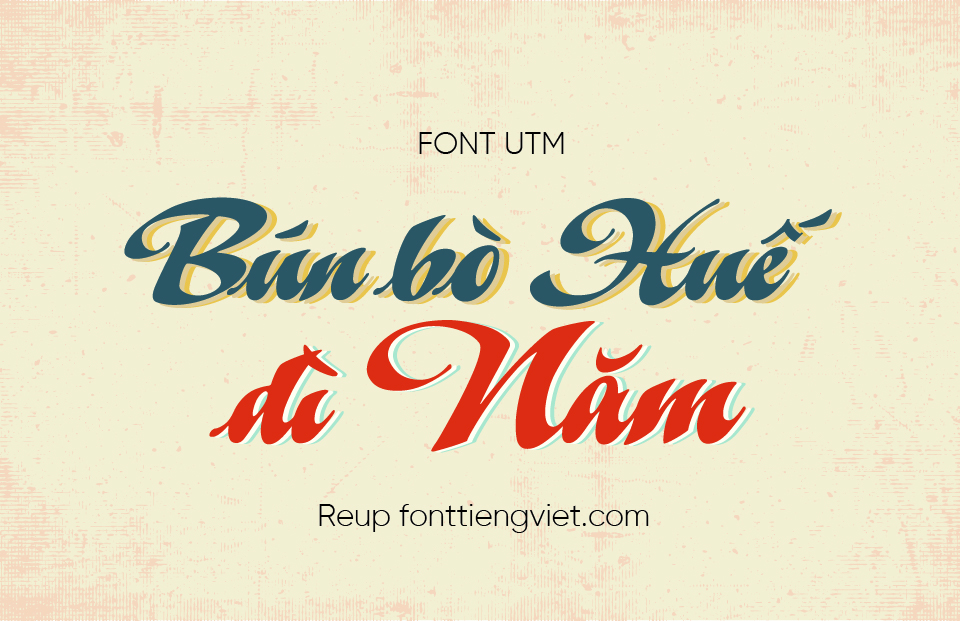
Giới thiệu về Font việt hóa UTM A&S Graceland
Trong thế giới đồ họa, việc lựa chọn một Font Chữ phù hợp đóng vai trò quyết định đến linh hồn của tác phẩm. Font việt hóa UTM A&S Graceland là một cái tên nổi bật trong bộ sưu tập UTM nổi tiếng tại Việt Nam. Đây là font chữ mang phong cách hoài cổ, lấy cảm hứng từ những bảng hiệu quảng cáo cổ điển của Mỹ. Với các đường nét uốn lượn mềm mại nhưng vẫn giữ được sự chắc chắn, bộ chữ này mang lại cảm giác sang trọng và đầy tính nghệ thuật cho mọi bản vẽ. Phiên bản này đã được việt hóa hoàn chỉnh, giúp người dùng dễ dàng sử dụng các ký tự tiếng Việt có dấu mà không lo lỗi font.
Tại sao nên chọn Font việt hóa UTM A&S Graceland?
Ưu điểm lớn nhất của Font việt hóa UTM A&S Graceland chính là tính thẩm mỹ độc đáo. Kiểu chữ này cực kỳ phù hợp cho các thiết kế tiêu đề, logo, bìa sách hoặc thiệp mời sự kiện. Đối với các bạn học sinh và giáo viên, font chữ này có thể dùng để trang trí báo tường hoặc làm nổi bật các slide thuyết trình bài giảng. Sự kết hợp giữa nét thanh và nét đậm tạo nên một nhịp điệu thị giác bắt mắt, giúp nội dung truyền tải trở nên ấn tượng và dễ đi vào lòng người hơn.
Ứng dụng thực tế trong giáo dục và thiết kế
Trong môi trường học đường, font chữ này giúp các sản phẩm sáng tạo của học sinh thêm phần chuyên nghiệp. Bạn có thể dùng nó để thiết kế áo lớp hoặc làm tiêu đề cho các dự án học tập nhóm. Hy vọng bài viết này giúp bạn hiểu rõ hơn về giá trị của Font Miễn Phí, Font Việt Hóa, Font việt hóa UTM A&S Graceland trong công việc hằng ngày.